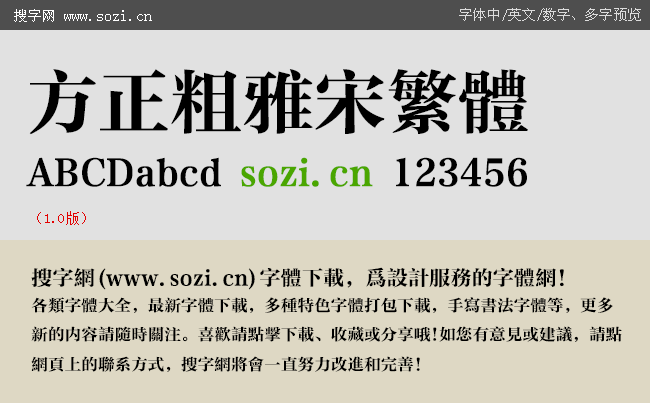
方正粗雅宋繁體(FZCYSFW)
搜字網(wǎng)提供一款方正粗雅宋繁體中文字體下載,方正粗雅宋繁體是一款字形清秀的中文字體,該字體端正大方,結(jié)構(gòu)清晰,效果出眾,常用于產(chǎn)品設(shè)計(jì)、包裝印刷、報(bào)刊雜志、正文標(biāo)題、繪畫(huà)創(chuàng)作等廣告設(shè)計(jì)場(chǎng)合使用。